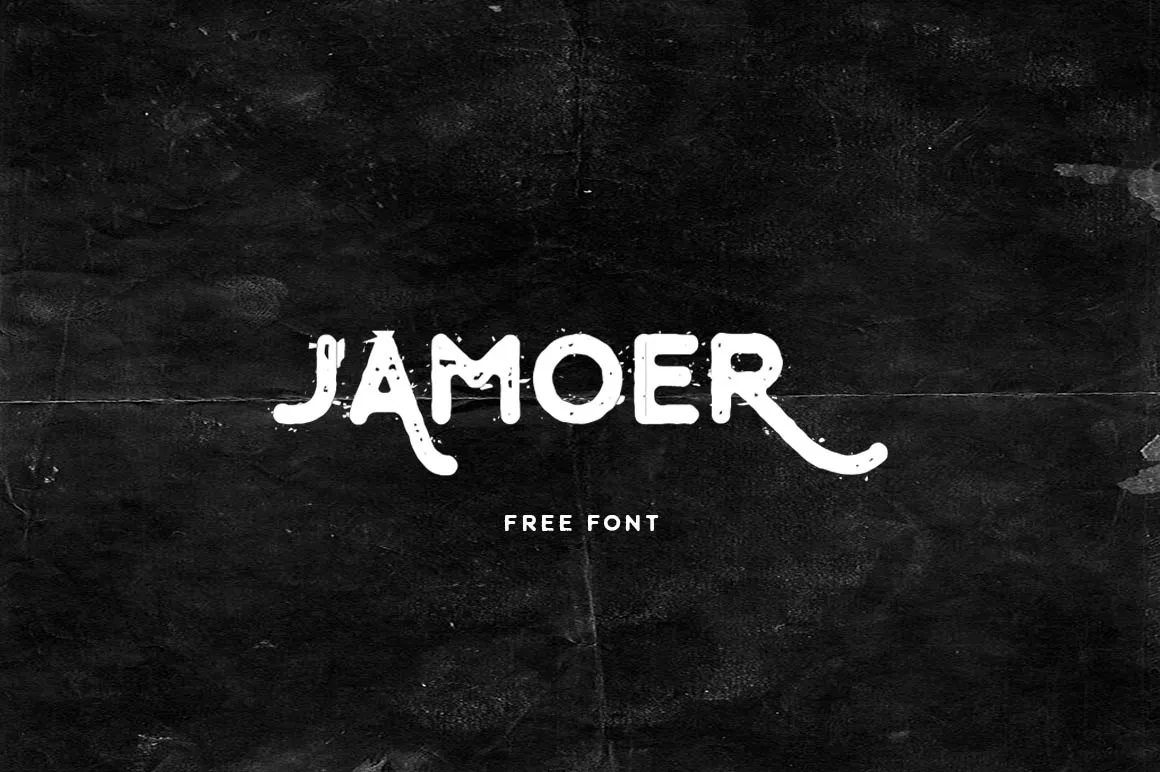
Jamoer Font – Fonte Grátis
Jamoer Font
A Jamoer Font é uma elegante tipografia blackletter que traz um toque vintage único ao seu design. Criada por Bagus Budiyanto, esta fonte customizada se destaca por sua riqueza de detalhes e estilo retro, perfeitamente adaptável para trabalhos artísticos vintage. Perfeita para designers apaixonados por uma atmosfera elegante e sofisticada, a Jamoer Font oferece um conjunto amplo de opções que vão do básico ao ornamental, tornando-a uma escolha ideal tanto para o design gráfico quanto para criações literárias. Descarregue a fonte agora e experimente sua versão única no seu próximo projeto, garantindo um toque distintivo e sofisticado à sua produção visual.